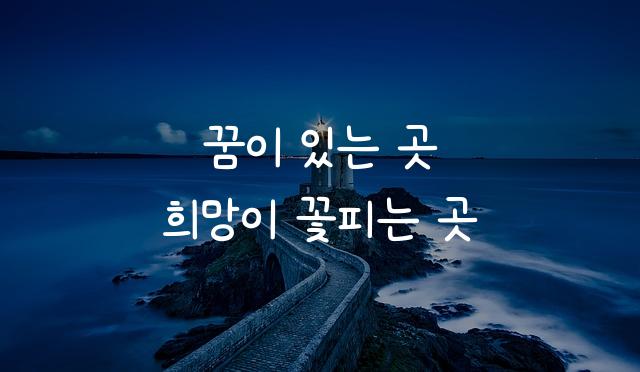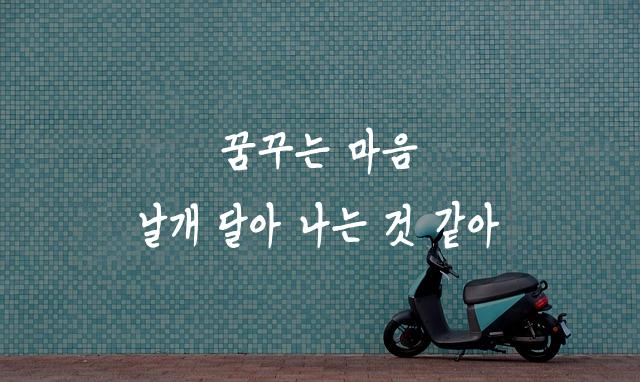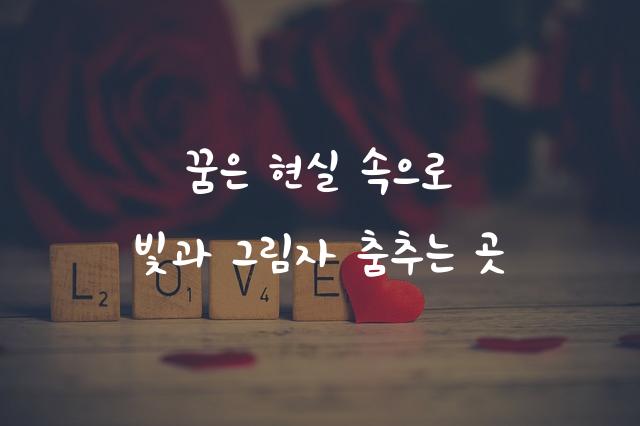
인천교육자람체는 인천광역시교육청에서 제작한 캘리그라피 스타일의 폰트로, 펜으로 쓴 듯한 기울어진 글씨가 특징입니다. 이 폰트는 우아하면서도 개성 있는 필기체의 감성을 담고 있습니다.
인천교육자람체은(는)
손글씨, 펜/붓터치, 기울임, 감성적인 계열의 생김새를 가지고 있으며
교육 자료, 어린이 책, 보고서/문서 등에서 자주 활용되며, 효과적인 메시지 전달에 적합합니다.
이 폰트는 교육, 출판/미디어, 유아/가족 분야에 잘 어울리며,
친근한, 부드러운, 편안한 느낌을 담고 있는 것이 특징입니다.